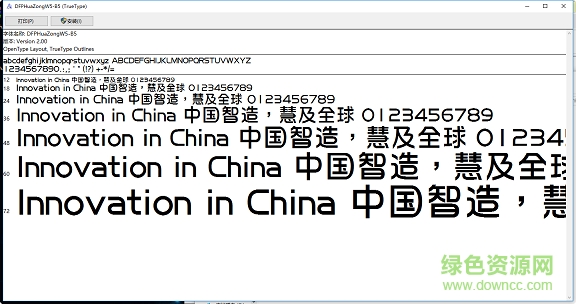
dfhuazong-w5-winp-bf字體又叫華康華綜體,是一款字形優(yōu)美的經(jīng)典字體,細(xì)節(jié)精致,特征鮮明,富于情趣,具有一種古風(fēng)韻味,喜歡的朋友歡迎免費(fèi)下載!
猶如手繪POP的美工字體,直筆、橫筆粗細(xì)接近,偏旁右側(cè)圓弧表現(xiàn),左側(cè)則邊角切齊,筆劃特色顯著,端正中又帶著活潑俏皮感。適合于內(nèi)文及各式標(biāo)題上使用。